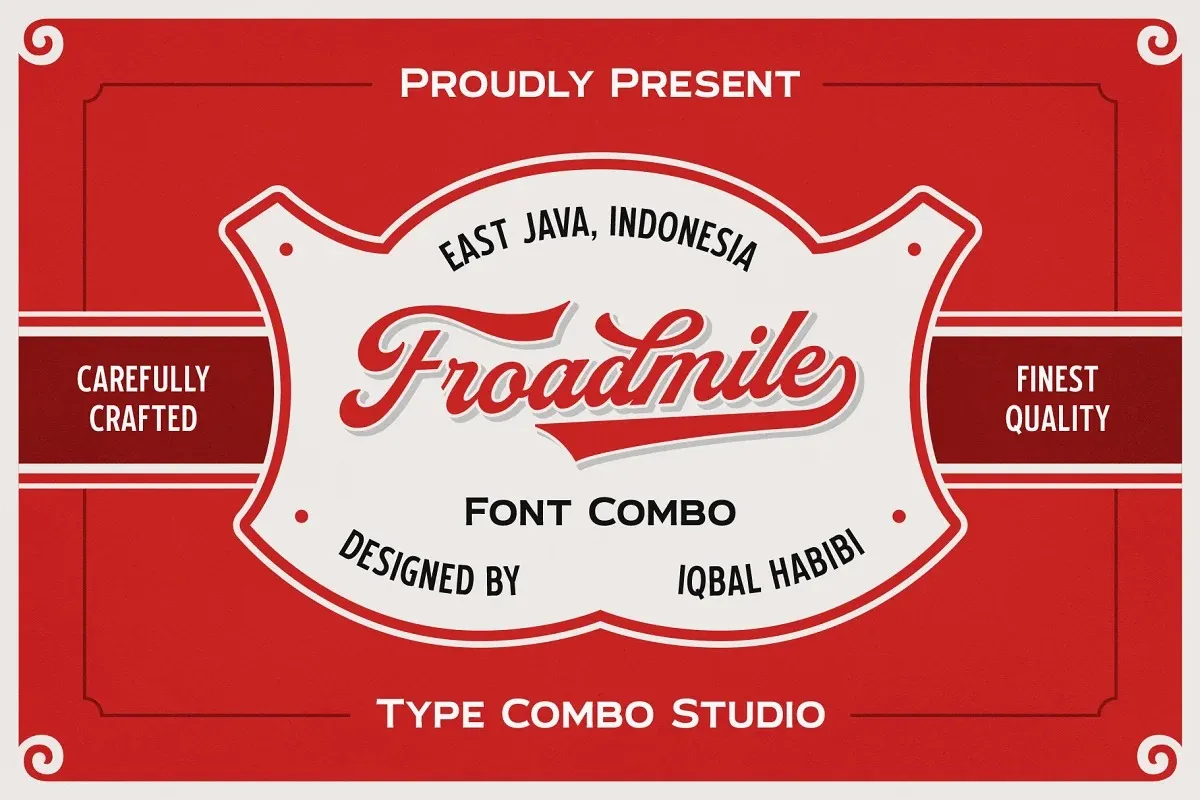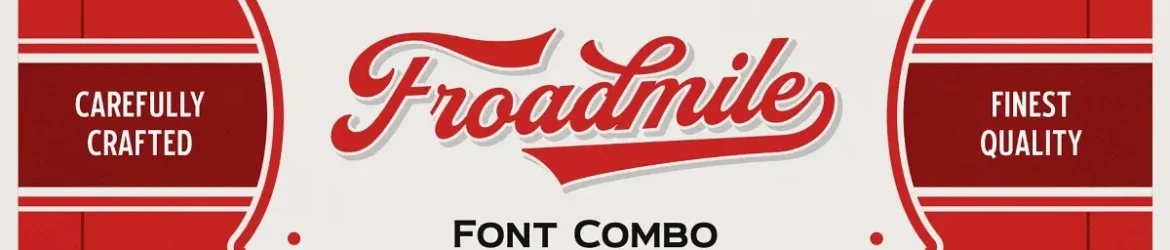
Esta font é uma elegante escolha para qualquer designer que busca estilizar sua arte com um toque vintage dos anos 60. Inspirada no estilo script, esta font inclui variantes de tipo sem serif e compacto, oferecendo flexibilidade para criar combinações icônicas e modernas. Perfeita tanto para projetos tradicionais quanto para versões mais antigas, a Froadmile Font é uma opção ideal para aqueles que desejam incorporar um toque nostálgico ao seu trabalho de design. Para tornar o processo de criação ainda mais simples e eficaz, a Froadmile – Font Combo oferece extras como logomarcas personalizadas e modelos de layout. Estes recursos adicionais são perfeitos para auxiliar em qualquer projeto gráfico que você possa estar desenvolvendo, seja ele moderno ou vintage. Com a Froadmile Font e seu complemento, seus design projetos terão um toque único e atualizado.